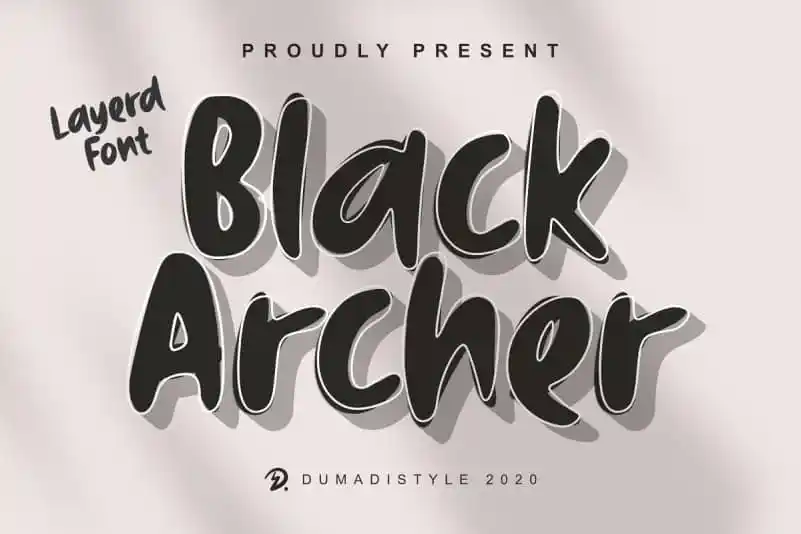
Black Archer Display Font – Download Grátis
A Black Archer Display Font é uma fonte feita com tinta a óleo autêntica que adiciona camadas de linhas e sombras. Esta elegante escolha de fontes é ideal para seus projetos criativos, como logotipos, citações impressas, convites, cartões postais, embalagens de produtos, cabeçalhos, logo, papelaria, posters e design de roupas. A Black Archer é perfeita para quando você está buscando um estilo visual forte e moderno que complementa os detalhes com uma delicada trama de sombras. Através da Black Archer, as pessoas poderão criar designs impactantes que se destacam em qualquer mídia impressa ou digital.